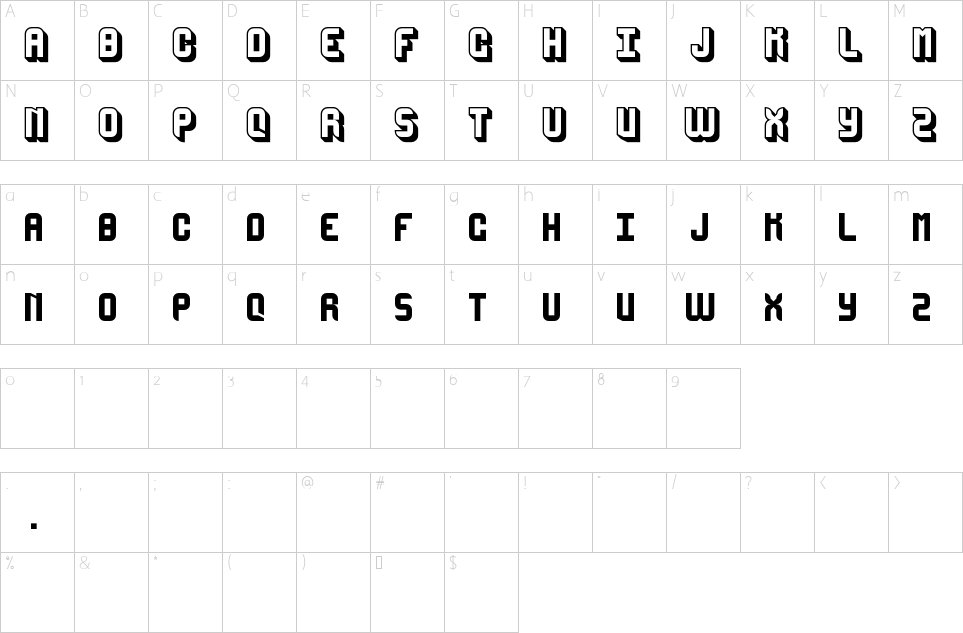
Aqui está uma descrição em português para a página de download da fonte ‘Mega Sans Font | 1001 Free Fonts’: A fonte ‘Mega Sans’ é uma opção moderna e elegante para designers e criadores de conteúdo. Desenvolvida pela Skyhaven Fonts, ela é uma fonte gráfica com linhas suaves e harmoniosas, ideal para criar rótulos, letras de música, títulos em blogs ou qualquer tipo de design onde o estilo e a legibilidade são importantes. Com seu design minimalista e arrojado, ‘Mega Sans’ oferece uma ampla gama de opções de personalização, permitindo que você personalize a fonte para atender às suas necessidades específicas. Disponível tanto para Windows quanto para Mac, a fonte ‘Mega Sans’ é um excelente investimento para qualquer biblioteca de fontes. Até agora, ela foi baixada mais de 16.317 vezes, evidenciando sua popularidade e qualidade. Com ela, você pode adicionar um toque único e profissional a qualquer projeto visual.